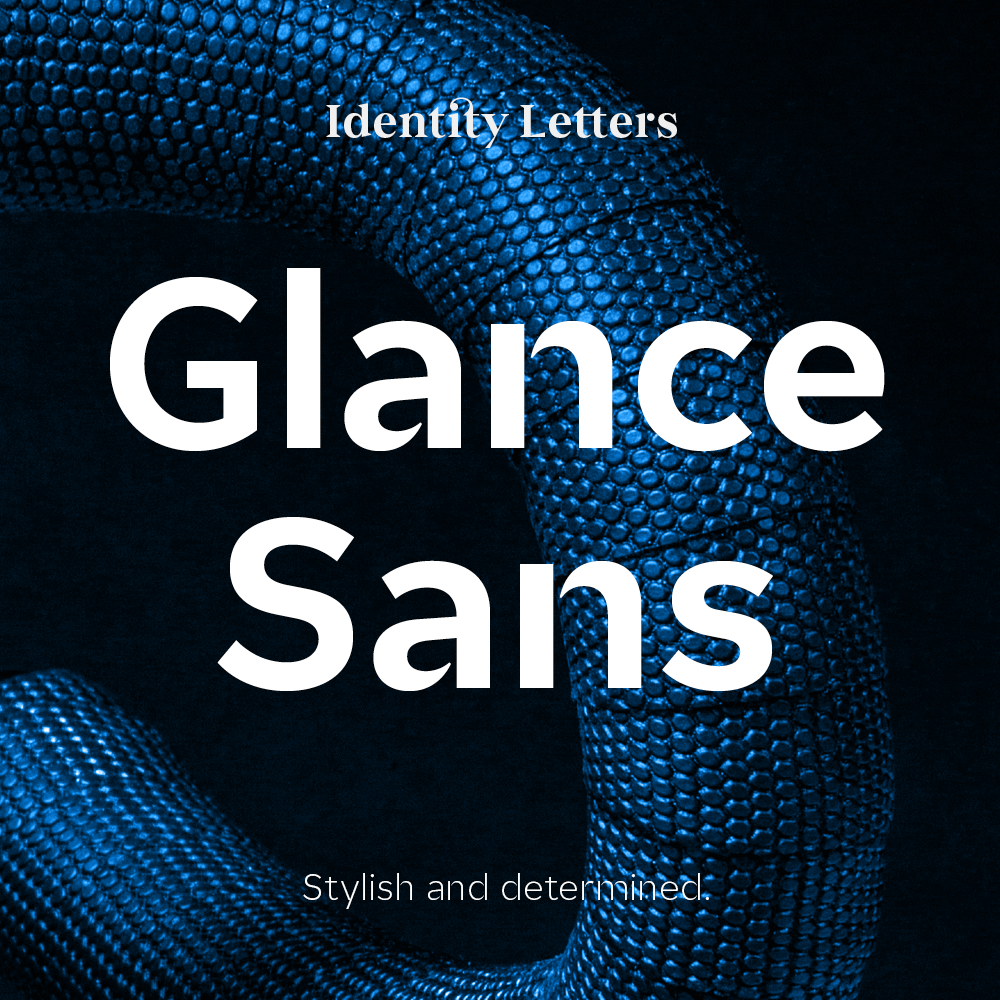
[Mitglied R::b…] Geschrieben November 24, 2022 Teilen Geschrieben November 24, 2022 (bearbeitet) Nachtrag: In der Abbildung erscheint mir das Kerning an manchen Stellen etwas holprig und ich bin mir auch nicht sicher wie gut die Strichstärken aufeinander abgestimmt sind. Aber es ist sicher jedem klar, dass man bei dem Preis hier und da Abstriche machen muss. Unterm Strich würde ich sie aber schon mal zu einer der besseren Latinotype-Fontfamilien zählen und der Ausbau ist natürlich fantastisch. Wer also eine kostengünstige Franklin-Alternative – noch dazu mit ẞ sucht, wird hier denke ich fündig. bearbeitet November 24, 2022 von R::bert 1 1 Link zu diesem Kommentar
[Mitglied Oliv…] Geschrieben November 26, 2022 Teilen Geschrieben November 26, 2022 Paypal ändert ab und zu die Zahlungsabwicklung. Wenn man da als Entwickler nicht mithält, holpert es leicht. 1 Link zu diesem Kommentar
[Mitglied Phoi…] Geschrieben November 27, 2022 Teilen Geschrieben November 27, 2022 Erneut verschenkt Eldamar Studios ein Paket, diesmal fünfhundert Photo-Overlays, via sharewareonsale: https://sharewareonsale.com/s/free-500-realistic-professional-photo-overlays-100-discount Link zu diesem Kommentar
[Mitglied Micr…] Geschrieben November 29, 2022 Teilen Geschrieben November 29, 2022 Am 25.11.2022 um 11:00 schrieb Norbert P: *)… die entsprechende Email ist natürlich schon raus. Die reagierten beim letzten Mal auch prompt. Aber der Umweg müsste ja eigentlich nicht sein. Hast du schone eine Rückmeldung bzw. die Fonts bekommen? Bei mir hat sich leider noch nichts getan ... Link zu diesem Kommentar
[Mitglied Norb…] Geschrieben November 29, 2022 Teilen Geschrieben November 29, 2022 … bei mir auch nicht, ich schicke in zwei Tagen wohl die nächste Email hinterher. Das letzte Mal ging's irgendwie besser. Link zu diesem Kommentar
[Mitglied Micr…] Geschrieben November 29, 2022 Teilen Geschrieben November 29, 2022 Ich habe es gerade noch einmal über das Kontaktformular probiert. Wenn sich bis morgen niemand meldet gehe ich über PayPal ... Link zu diesem Kommentar
[Mitglied Norb…] Geschrieben Dezember 1, 2022 Teilen Geschrieben Dezember 1, 2022 Heute kam eine Email mit der ZIP-Datei … Link zu diesem Kommentar